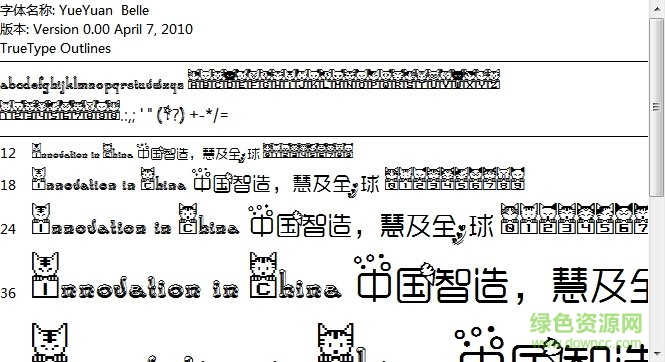
yueyuan belle常規(guī)字體是一款筆觸柔和而溫婉的兒童字體,充滿了童真童趣的活潑體驗,給人單純美好的閱讀體驗,歡迎大家來綠色資源網(wǎng)使用!
呆萌萌,稍顯笨拙但又透著一股可愛,直來直去從不拐彎抹角,在這個復雜的世界里保存著一份童真!
手寫字體一般給人清秀干凈的藝術(shù)字體美感,而天然發(fā)呆萌字體結(jié)合了卡通字體的特色,更顯得生動、憨態(tài)可掬,運用在兒童內(nèi)容的文字創(chuàng)意上更有愛哦!